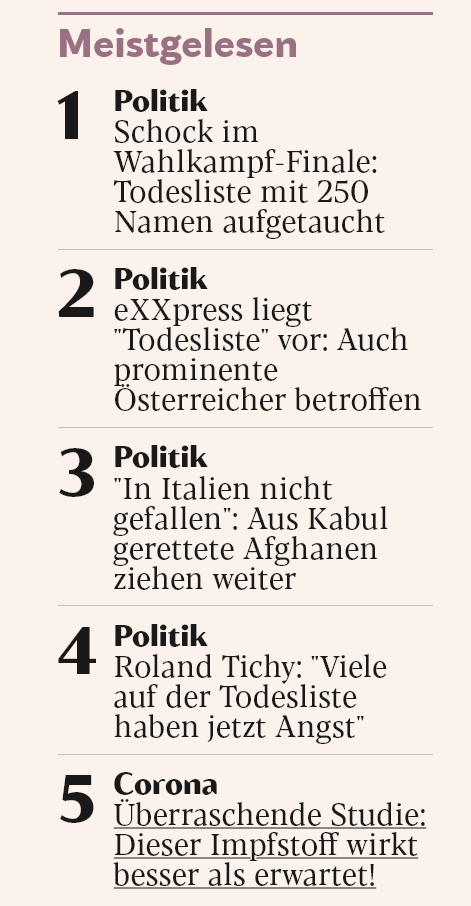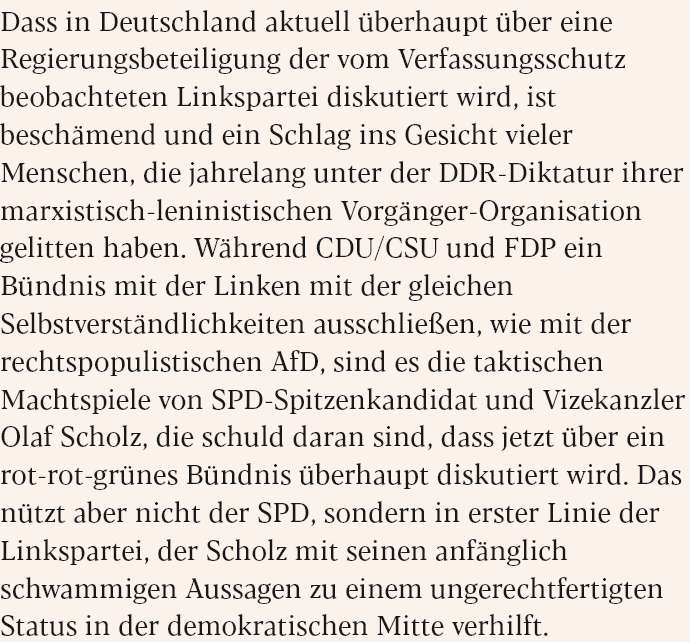
Webfont wackelt auf Grundlinie
bei mir auf dem Bildschirm (Windows/Fujitsu Notebook) "wackelt" die Schrift Blacker Pro auf der Grundlinie (siehe Screenshot). Fiel mir auch schon manchmal bei anderen Fonts auf. Auf dem Smartphone geht es jedoch.
Ist bei euch auch dieses Wackeln sichtbar, und kann mir jemand erklären, woran das liegt? (schlechtes Hinting, schlechte Grafikkarte/Monitor etc.). Zetafonts ist doch eine recht professionelle Foundry würde ich sagen ...
Ja, das ist das interne Hinting. Man muss da entsprechende Zonen definieren, damit die Render-Software weiß, dass die Rundungen, die bei hoher Auflösung optisch unter die Grundlinie hinausgehen müssen, bei kleiner Auflösung mit den geraden Lettern abschließen.
Kann im Zweifel natürlich auch von den konkret benutzten Webfont-Formaten und deren Generierung abhängen, selbst wenn es im Original-DTP-Font korrekt angelegt war.
Dann haben also die Font-Engineers gepfuscht ... Dass das bei dieser Web-Zeitung niemandem auffällt?!
Naja, da gibt es noch andere Mängel: Der Zeilenabstand ist an einigen Stellen (z.B. im Impressum) auch ganz schön „sparsam“.